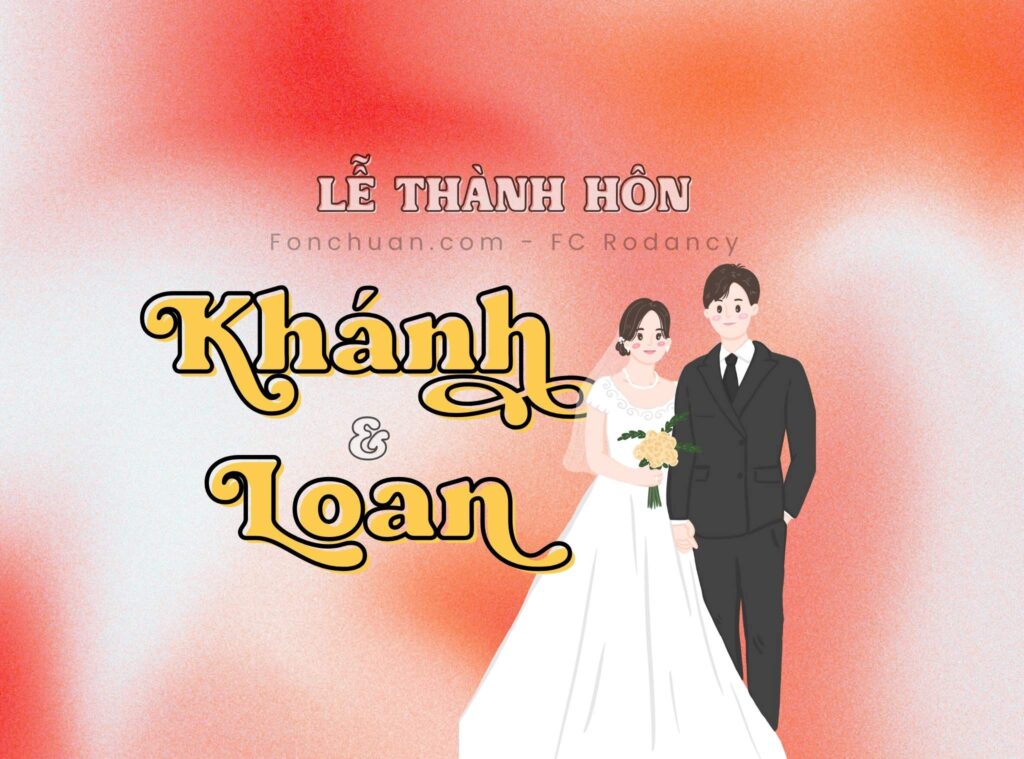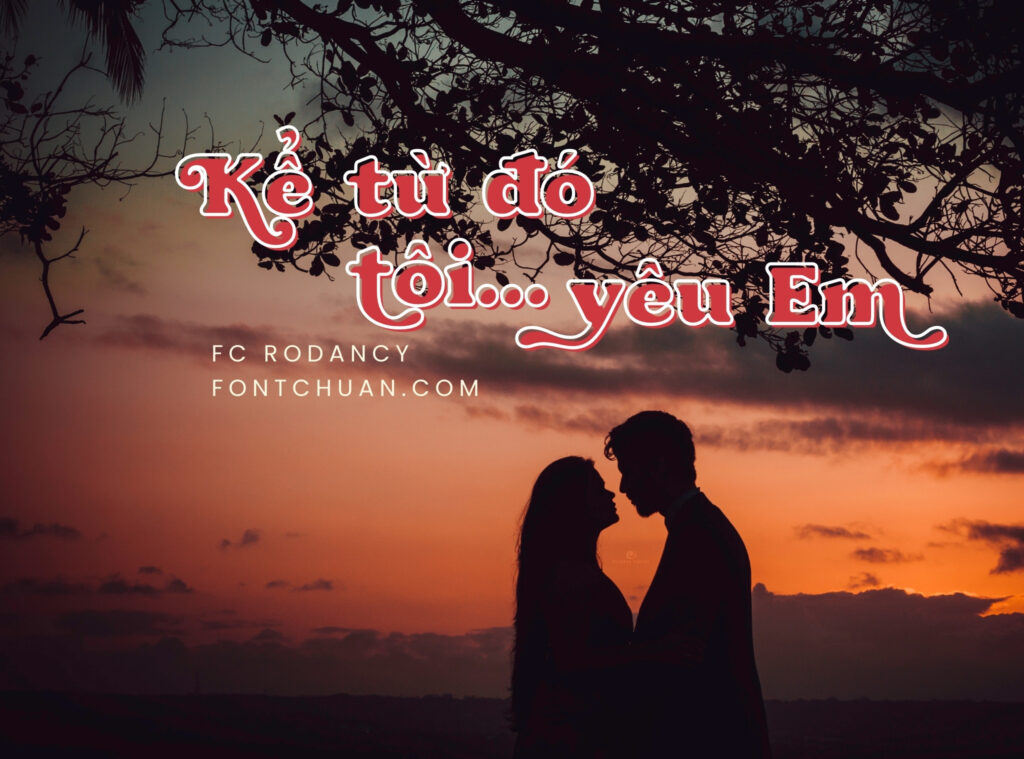
Font FC Rodancy Việt Hóa
Tác giả Font: Yudi Pratama Chandra
Font Rodancy là một kiểu chữ serif phong cách retro và đậm nét, được thiết kế bởi Yudi Pratama Chandra trực thuộc RantautypeStudio™. Với các đường cong dày và hình dạng bo tròn, Rodancy mang lại cảm giác mềm mại và thoải mái, gợi nhớ đến phong cách thiết kế những năm 70. Font này hỗ trợ đa ngôn ngữ, bao gồm tiếng Anh, Java, Ý, Cebuano, Malagasy, Swahili, Filipino, Afrikaans, Catalan, Pháp, Đức, Bồ Đào Nha, Thụy Điển và Tây Ban Nha.
Về đặc điểm thiết kế, Rodancy sở hữu các nét chữ dày dặn, bo tròn, tạo nên sự nổi bật và thu hút cho các dự án sáng tạo. Font này phù hợp cho nhiều ứng dụng như thiết kế logo, tiêu đề, bìa sách, thương hiệu, thiệp mời, cưới hỏi và các dự án thiết kế mang phong cách vintage hoặc retro. Các ngành nghề như quảng cáo, thiết kế đồ họa, thời trang và truyền thông có thể tận dụng “Rodancy” để tạo ra những sản phẩm ấn tượng và độc đáo.
Ngoài ra, với phong cách bo tròn và mềm mại, Rodancy còn có thể ứng dụng làm font chữ Trung Thu cho poster, banner hay bao bì sản phẩm mùa lễ hội, mang lại cảm giác hoài niệm nhưng vẫn hiện đại.